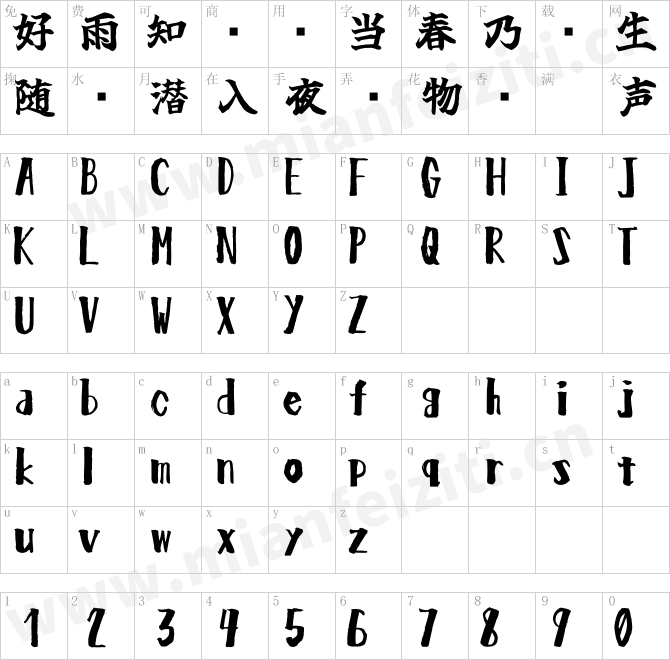
玉ねぎ楷書激無料版v6
玉葱楷書激無料版是简单的手写笔刷字体洋葱正本字体的稍微激烈的版本,它是为视频,同人志,新年贺卡等各种场景而创建的字体。
此字体为免费版(JIS一级汉字+α)
【收录文字】
345 个全角字符(平假名、片假名、012、ABC、abc、希腊语、俄语)
符号233字(?〆㈱【】{}@*※→†√⑳Ⅸ㌍㎞)
半角157个字符(ABCabc片假名!?*{}[]./@#$%)
JIS一级汉字,共2965个字符
大约几个可能用于创作的汉字组合,您可以自行选择。